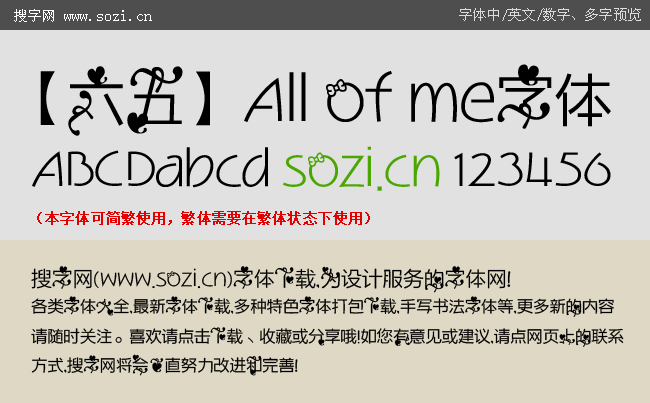
All of me字體
搜字網(wǎng)給大家提供一款A(yù)ll of me字體手機(jī)中文字體下載。這款手機(jī)字體是以黑體字體為原形,在字體間嵌入了花紋圖案。具有黑體端正易認(rèn)的風(fēng)格,又很有趣味性,特別適合喜歡手機(jī)字體個性一些的朋友在手機(jī)上安裝使用。